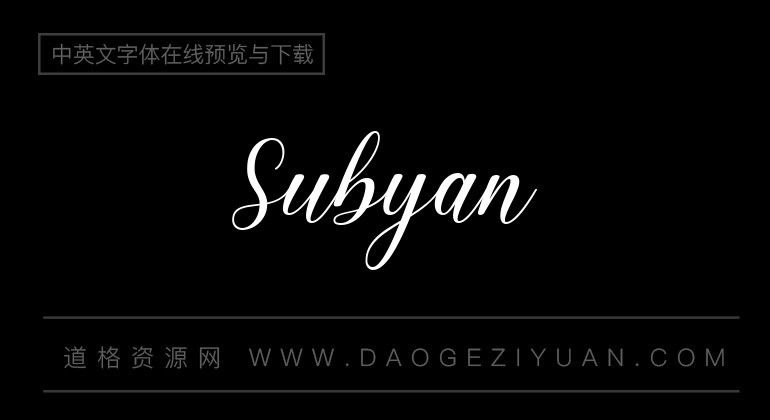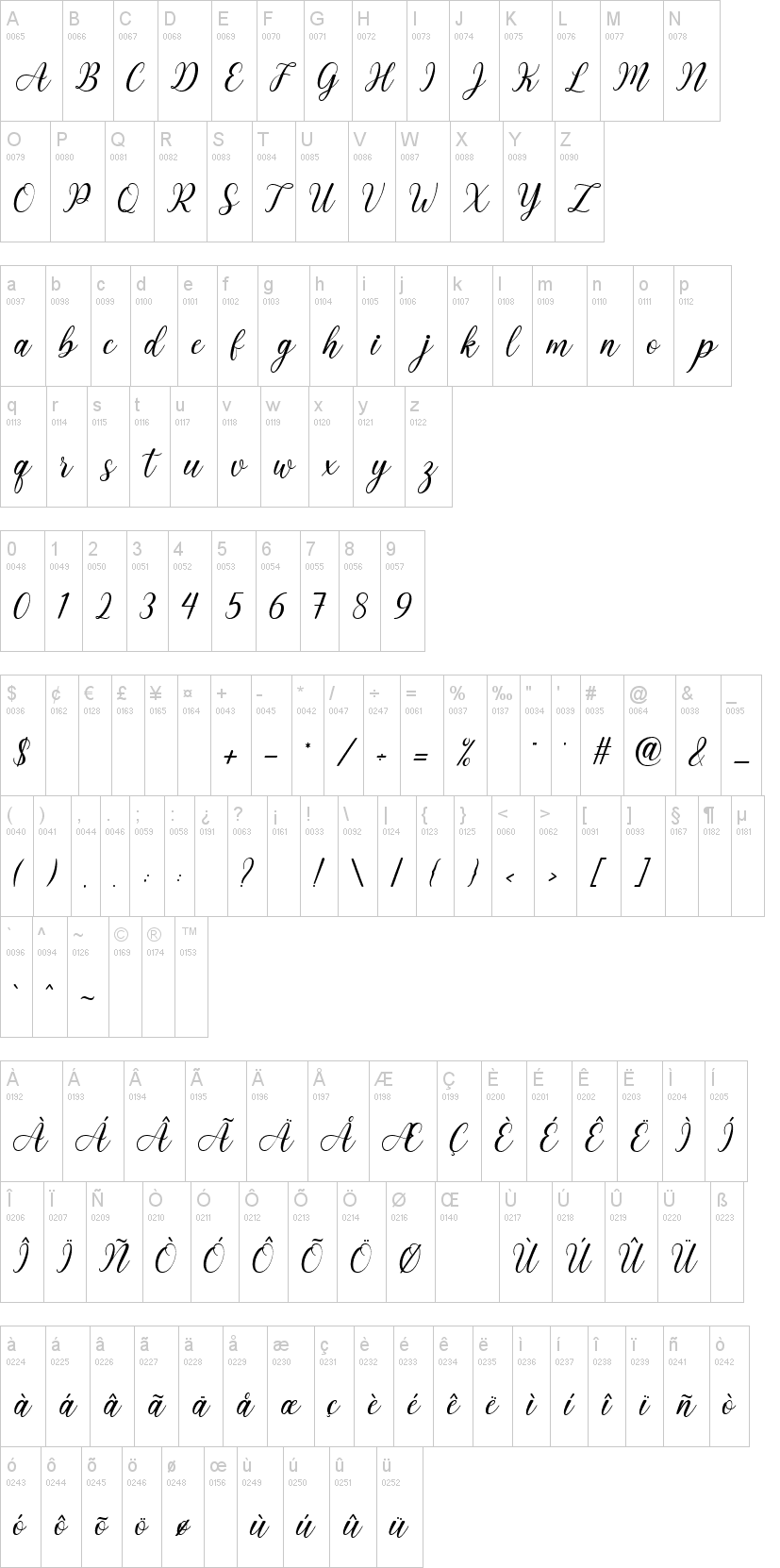
Subyan 字体是一种简约的英文字体,它由比利时设计师 Mika Melvas 创作,他将其称为“一种抽象的、简洁的、抽象的字体”。Subyan 的字体设计简洁而精美,它的字形比较平衡,笔画细腻,可以提供良好的可读性,并具有较强的视觉冲击力。它可以用于各种印刷品、网页、平面设计等,是一款优秀的英文字体。内容介绍
Subyan是一款非常不错的手写艺术字体,具有很好的视觉感,适合于文化类的宣传设计、商业类品牌的广告和产品包装设计以及个性化文字排版等较多场景。